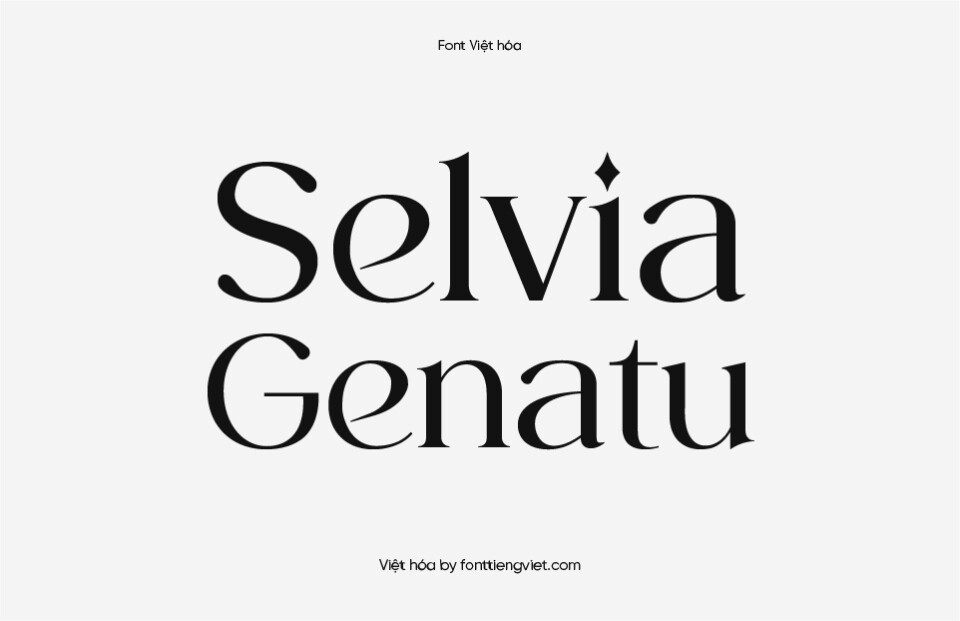
Font Việt hóa 1FTV VIP Selvia Genatu
Trong thế giới thiết kế đồ họa hiện đại, việc lựa chọn một bộ font chữ phù hợp đóng vai trò quyết định đến sự thành công của một tác phẩm nghệ thuật. Đặc biệt đối với các bạn học sinh, sinh viên hay giáo viên đang tìm kiếm sự sáng tạo trong các bài thuyết trình và dự án học đường, Font Việt hóa 1FTV VIP Selvia Genatu nổi lên như một lựa chọn hàng đầu. Đây là bộ Font Miễn Phí đã được tối ưu hóa hoàn toàn cho bảng mã tiếng Việt, giúp loại bỏ hoàn toàn các lỗi hiển thị dấu phổ biến, mang lại trải nghiệm mượt mà và chuyên nghiệp nhất cho người sử dụng tại Việt Nam.
Khám phá vẻ đẹp độc đáo của Font Việt hóa 1FTV VIP Selvia Genatu
Bộ font này được đánh giá cao nhờ sự kết hợp hài hòa giữa nét cổ điển và hơi thở hiện đại. Những đường nét thanh thoát, mềm mại nhưng không kém phần chắc chắn của nó giúp tạo nên một diện mạo hoàn toàn mới cho các văn bản khô khan. Khi sử dụng Font Việt hóa 1FTV VIP Selvia Genatu, bạn sẽ nhận thấy sự tỉ mỉ trong từng nét chữ, từ độ cao cho đến khoảng cách giữa các ký tự đều được tính toán khoa học. Điều này không chỉ giúp nội dung dễ đọc hơn mà còn tạo ra một không gian thẩm mỹ đầy cảm hứng, giúp người xem dễ dàng tiếp nhận thông tin và ghi nhớ lâu hơn.
Tính ứng dụng linh hoạt trong giáo dục và sáng tạo
Không chỉ dừng lại ở các thiết kế chuyên nghiệp, bộ font này cực kỳ phù hợp cho môi trường học đường. Các em học sinh có thể dùng để làm tiêu đề bài báo tường, trang trí bìa tiểu luận hoặc thiết kế các tấm thiệp chúc mừng thầy cô. Trong khi đó, giáo viên có thể ứng dụng vào việc soạn thảo giáo án điện tử, làm cho bài giảng trở nên sinh động và thu hút sự chú ý của học trò. Sự đa dạng trong các biến thể của font cho phép người dùng linh hoạt chuyển đổi giữa các phong cách từ trang trọng, lịch sự đến trẻ trung, năng động mà vẫn giữ được sự đồng nhất cho toàn bộ tài liệu.
Lý do bạn nên lựa chọn Font Việt hóa 1FTV VIP Selvia Genatu ngay hôm nay
Một trong những điểm mạnh lớn nhất của Font Việt hóa 1FTV VIP Selvia Genatu chính là khả năng tương thích tuyệt vời trên nhiều phần mềm khác nhau. Dù bạn đang sử dụng Microsoft Word để soạn thảo văn bản đơn giản hay dùng Adobe Photoshop, Illustrator để thiết kế chuyên sâu, bộ font này luôn hoạt động ổn định. Ngoài ra, việc đã được việt hóa kỹ lưỡng giúp các ký tự có dấu như “ă”, “â”, “đ” hay các dấu thanh không bị biến dạng, giữ nguyên được ý đồ nghệ thuật của nhà thiết kế gốc. Đây là yếu tố cực kỳ quan trọng để đảm bảo tính chuyên nghiệp và sự chỉn chu cho mọi sản phẩm mà bạn tạo ra.
Kết luận về bộ Font Việt hóa 1FTV VIP Selvia Genatu